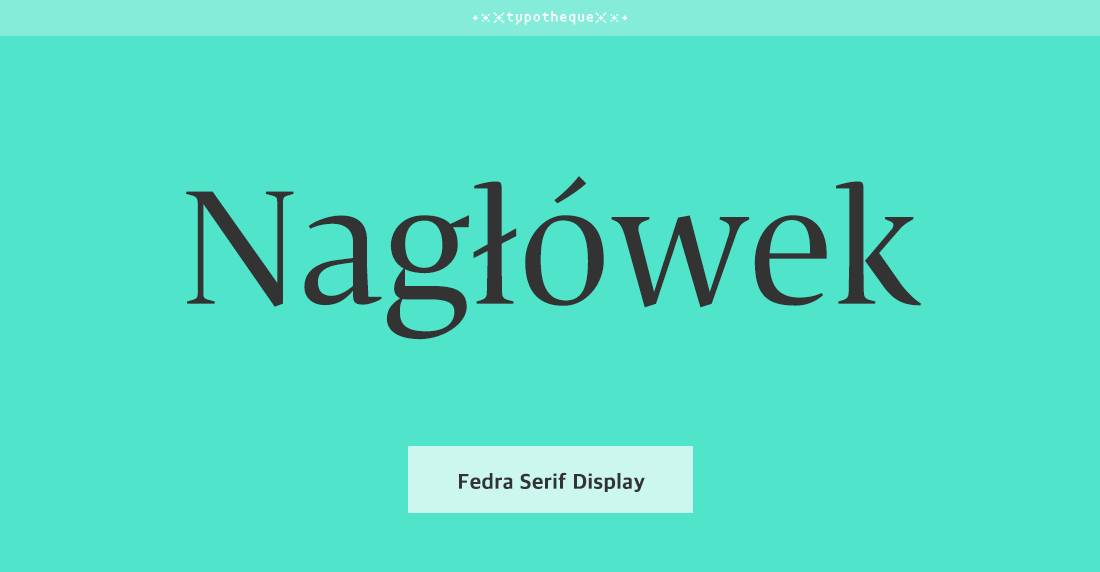
- Fedra Serif Display Std는 Fedra의 텍스트 버전을 보완해 디자인 된 폰트이다.
편집 디자인에 적합하게끔 만들어졌으며 특히 종이신문이나 카탈로그 등의 힘있는 헤드라인 서체로 사용하기 좋다.
폰트 정보 구분 명조 디자인디렉팅 Peter Biľak, Nikola Djurek 출시년도 2006